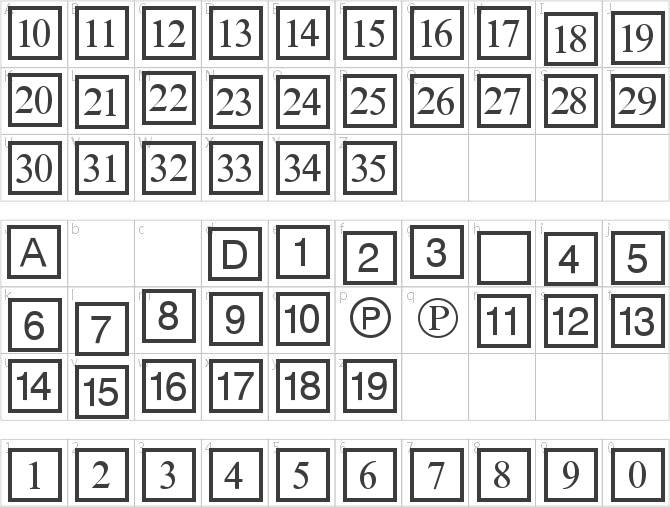
CD-Numbers 詳情頁
字體名稱: CD-Numb
CD-Numbers
CD-Numbers介紹
CD-Numbers字體字庫是一款讓人賞心悅目、百看不厭的英文字體,適合各類廣告和產品包裝設計應用,字體大小0.03MB,格式為ttf字體,上傳用戶是凡客,作者/版權方為未知
CD-Numbers效果圖